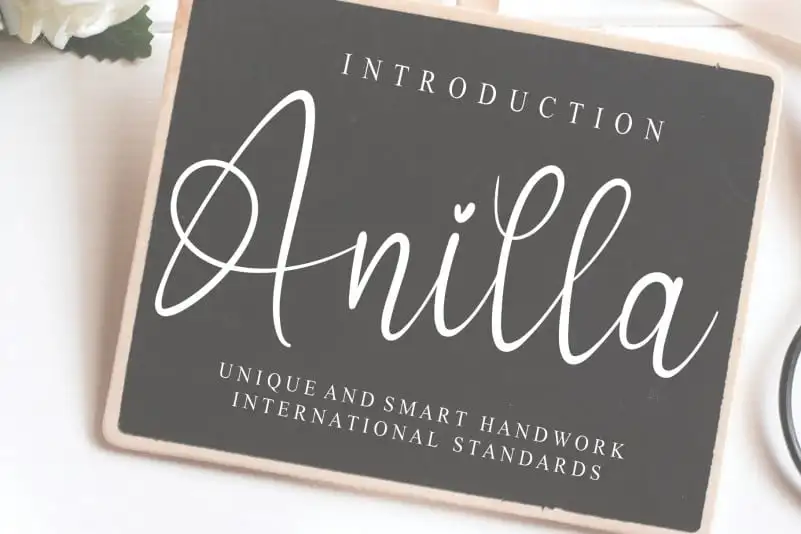
Anilla Script Font – Fonte Grátis
Anilla Script Font
Anilla Script Font é uma elegante fonte francesa criada pela designer creativeletter, perfeita para aqueles que buscam um toque delicado e sofisticado em seus projetos digitais. Com traços finos e movimentos fluidos, essa fonte é ideal tanto para design gráfico quanto para criação de conteúdo digital, fornecendo um visual único e autêntico. Seja para criar anúncios memoráveis, infográficos impactantes ou editoriais de alta qualidade, Anilla Script Font oferece o acabamento perfeito para qualquer projeto onde desejar agradar o olhar do seu público-alvo com detalhes cuidadosamente meticuloso. Com um design que vai além da simples estética visual, essa fonte criada pela creativeletter nos dá uma experiência única e especial que torna suas criações ainda mais memoráveis e encantadoras.